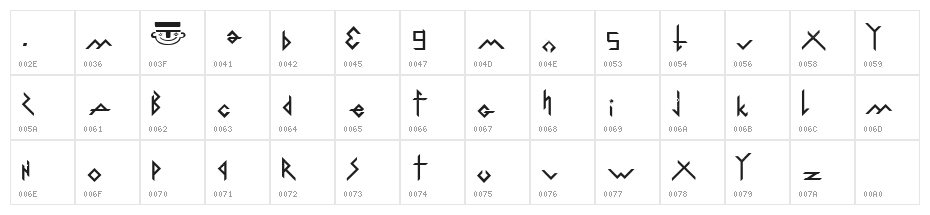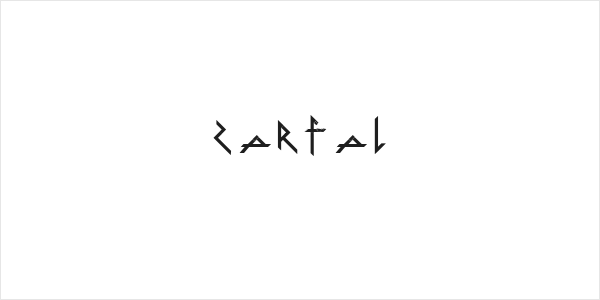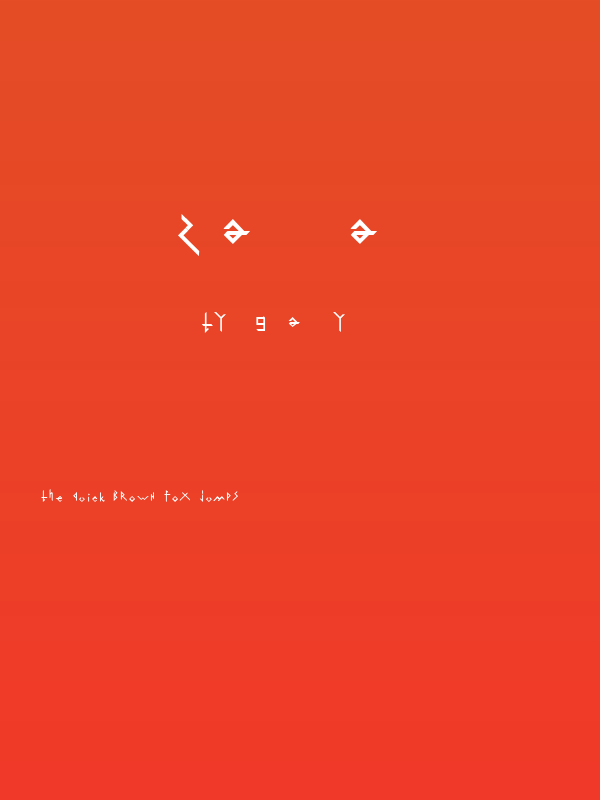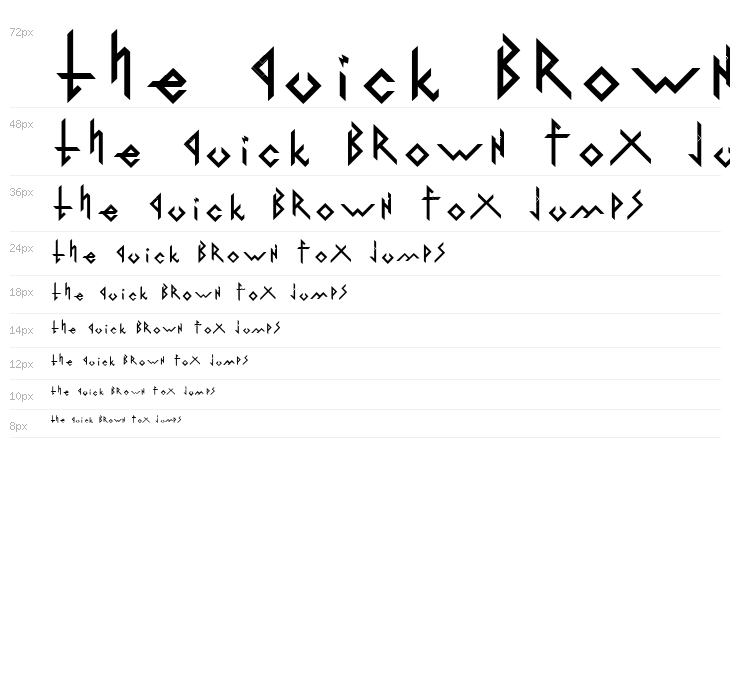
Zarfal Font
tricky
| Stile generale | Futuristic |
| Progetti proposti | Ideal for sci-fi themed projects, modern branding, video game titles, and futuristic posters. |